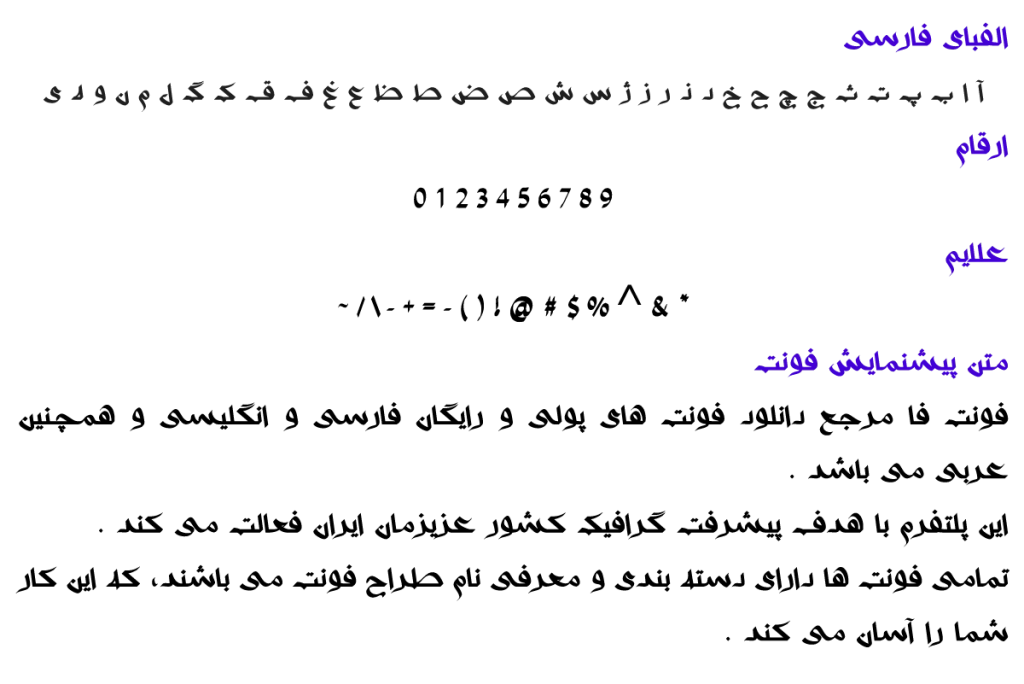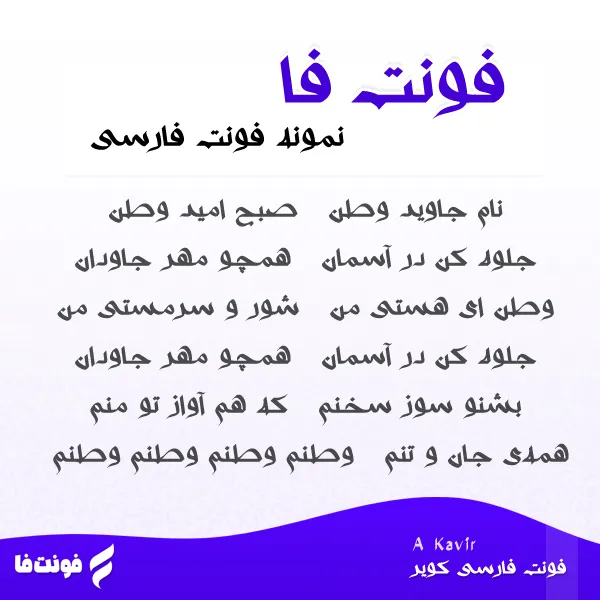
فونت فارسی کویر – A Kavir
سال ساخت فونت: 1391
طراح فونت: علی سواری نوع فونت: فونت هندسی
پیشنمایش فونت کویر
توضیحات و معرفی فونت کویر
فونت فارسی کویر ( A Kavir ) از مجموعه فونت های آزاد می باشد، و نیز نوع فونت هندسی می باشد.
فونت خوشگل مربوط توسط علی سواری در سال 1391 طراحی و ساخته شده است.
در تصویر زیر، شعر کهن «وطنم» با این تایپفیس به نمایش گذاشته شده است.